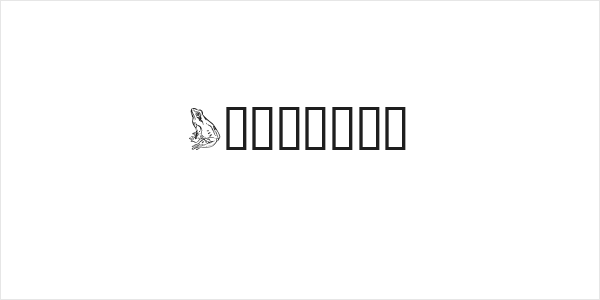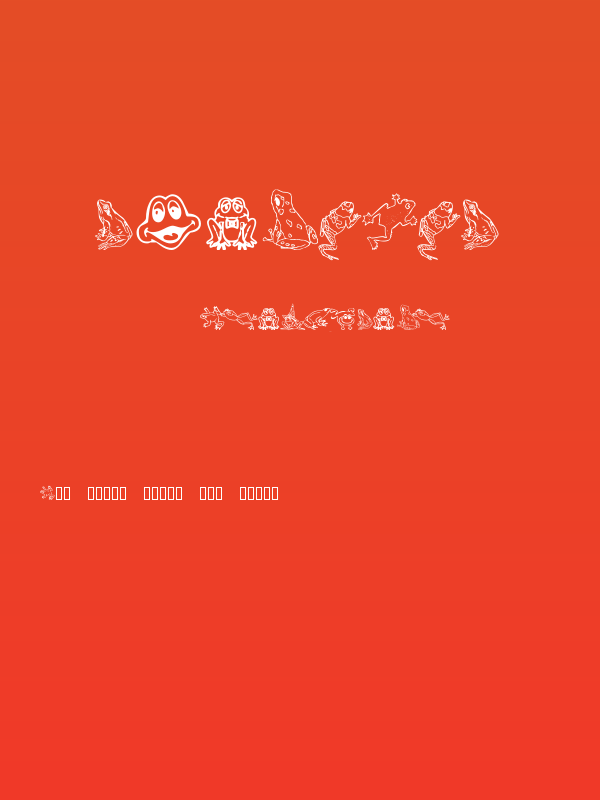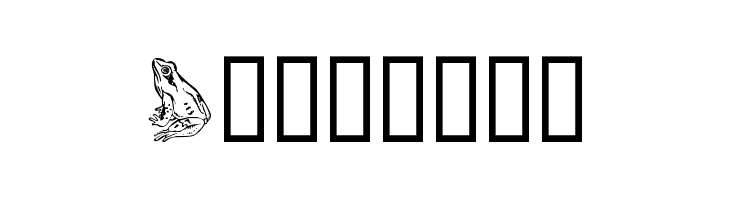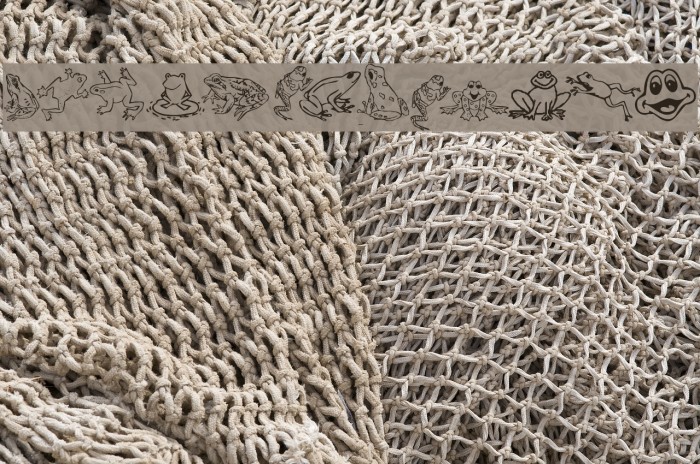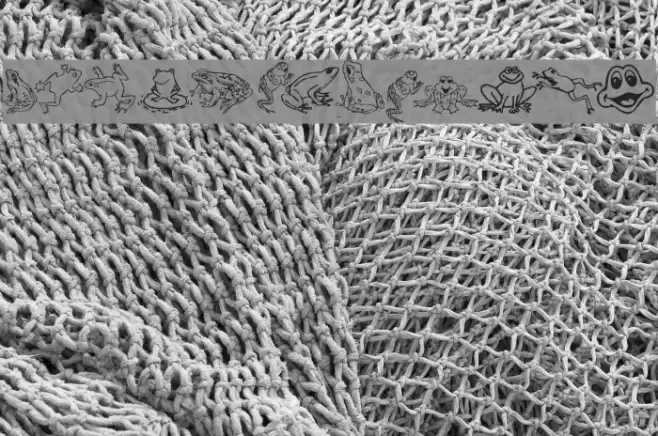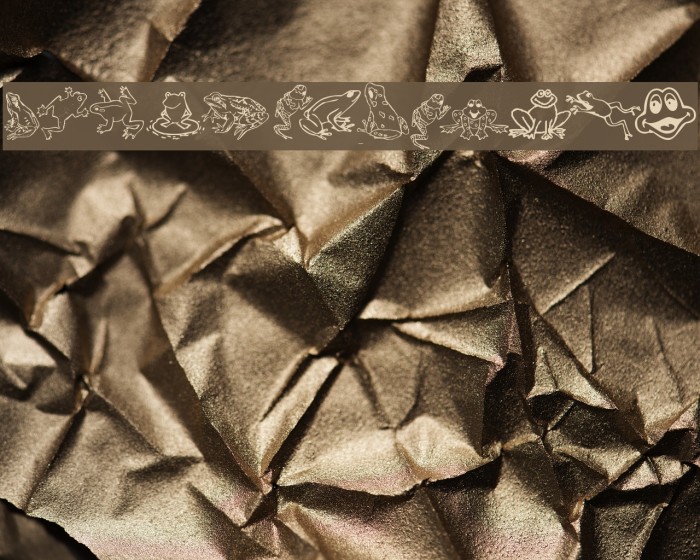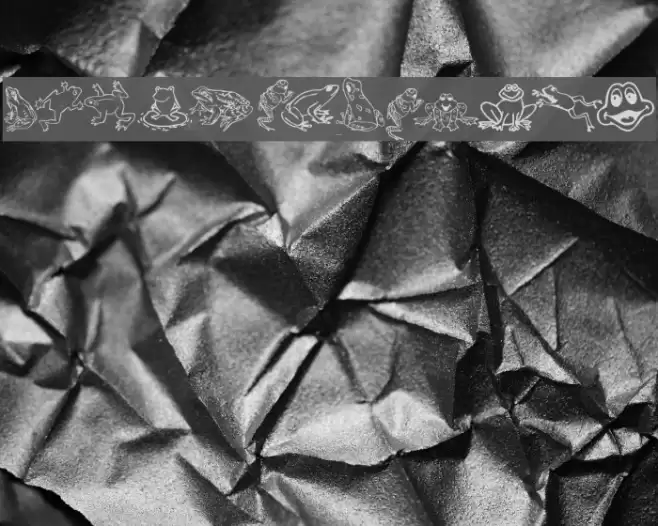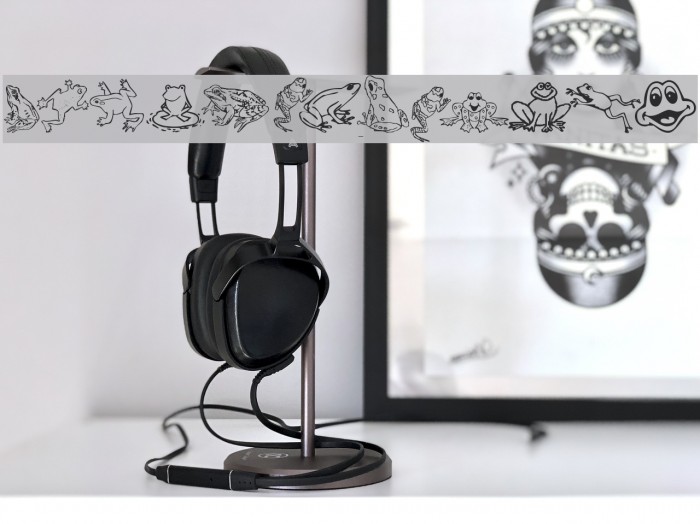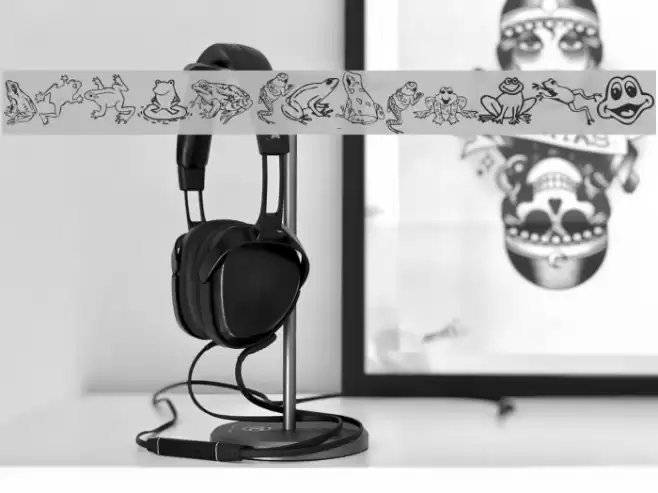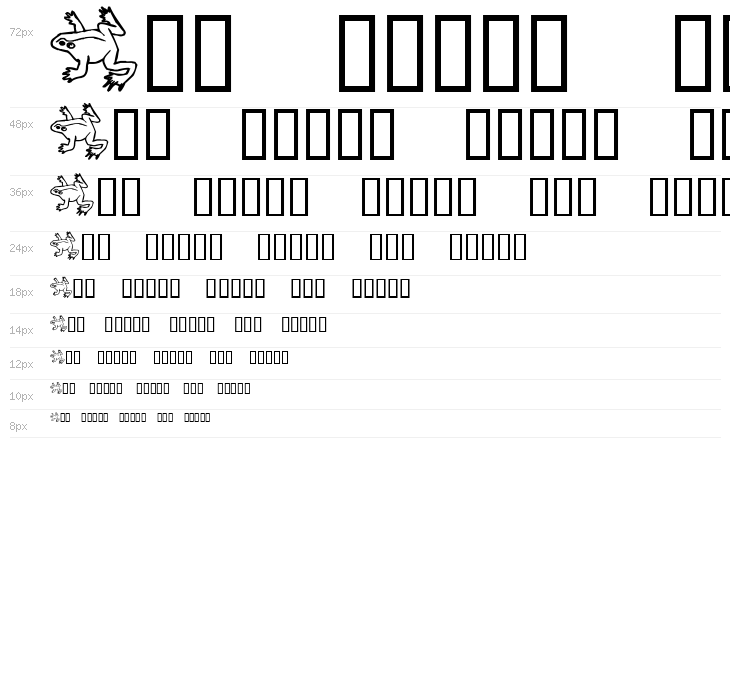
Amphibia Font
| Cas d'utilisation | Illustrations, Decorative elements |
| Projets proposés | Ideal for children's books, educational materials, or playful branding projects. |